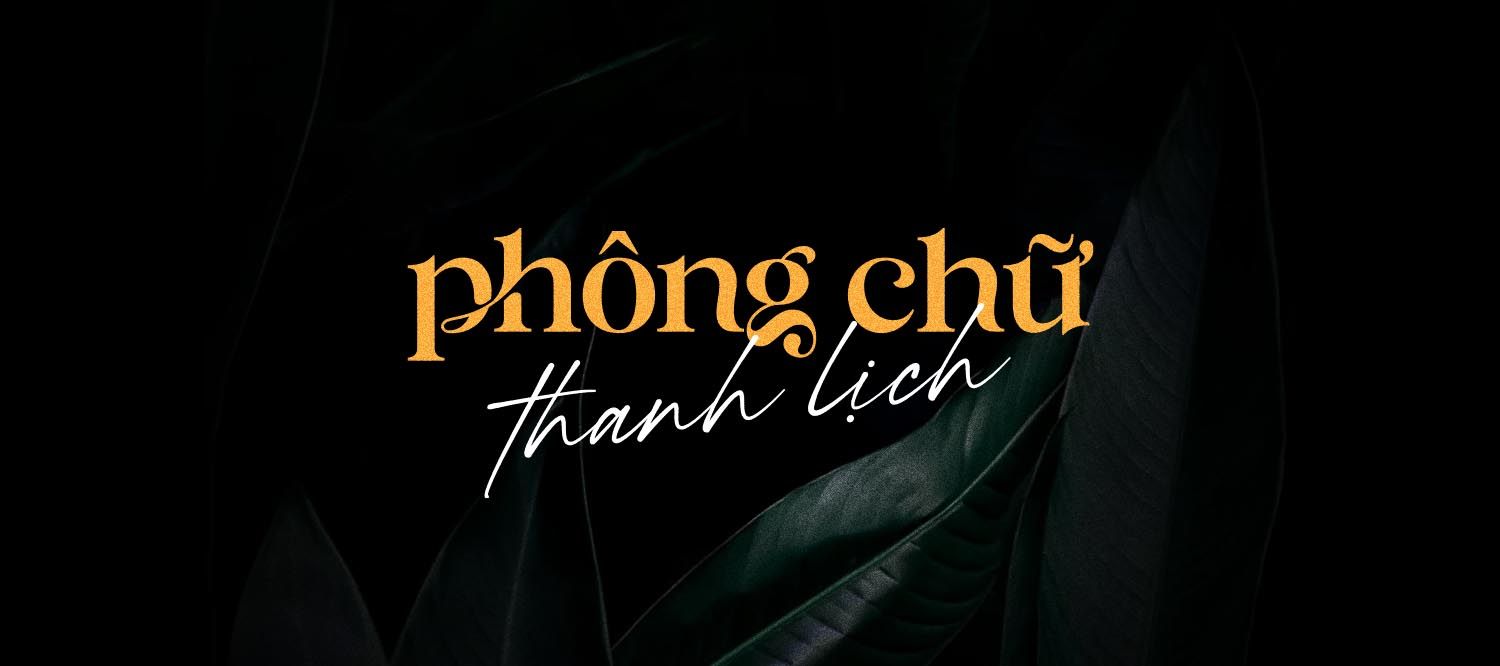
![[Tải Xuống] Bộ Font Chữ Làm Đẹp & Spa Kết Hợp Chữ Ký Viết Tay – Thanh Lịch, Tinh Tế & Cảm Xúc](https://cdn.s99.vn//cloud/X8XpseKt0H75yKqC.jpeg)
Trong lĩnh vực thiết kế thương hiệu, đặc biệt là các ngành liên quan đến spa, làm đẹp, mỹ phẩm hay thời trang, việc chọn lựa font chữ phù hợp đóng vai trò rất quan trọng. Một thiết kế chỉn chu, tinh tế cần đến sự kết hợp hoàn hảo giữa font chữ làm đẹp hiện đại và font chữ viết tay thanh mảnh, giúp truyền tải rõ nét tinh thần thương hiệu: vừa chuyên nghiệp, vừa gần gũi và đầy cảm xúc.
Bài viết hôm nay sẽ giới thiệu đến bạn một combo font chữ cực kỳ ăn ý: sự kết hợp giữa font serif hiện đại và font chữ chữ ký viết tay – như minh họa trong hình ảnh bạn đang xem. Đây là lựa chọn lý tưởng để áp dụng cho logo spa, tiêu đề mỹ phẩm, poster làm đẹp hay cả các ấn phẩm truyền thông cá nhân hoá.
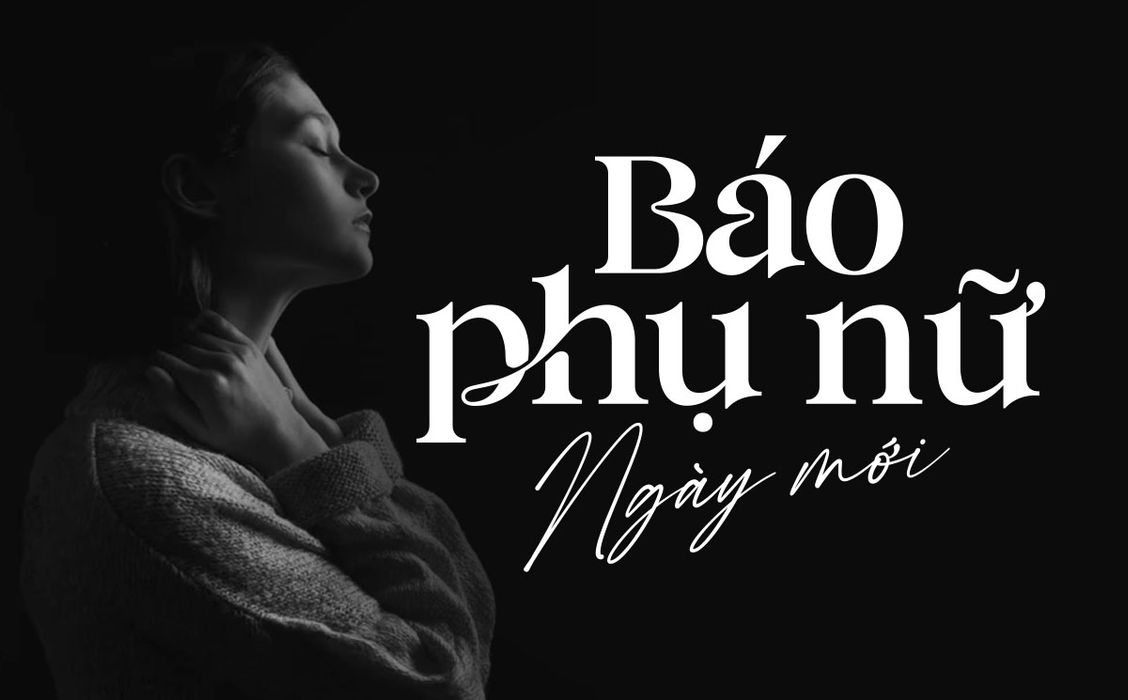
Font chữ chính được sử dụng cho tiêu đề là một kiểu serif hiện đại – một lựa chọn phổ biến trong thiết kế cao cấp. Điểm nổi bật của font này là có độ đậm ấn tượng giúp tiêu đề nổi bật, chân chữ chắc chắn nhưng tinh giản tạo cảm giác thanh lịch, cùng với cấu trúc chữ cái cân đối, dễ đọc và mang lại vẻ chuyên nghiệp.
Trong lĩnh vực spa – làm đẹp, kiểu chữ serif hiện đại là lựa chọn lý tưởng để truyền tải sự chuyên nghiệp và tinh tế. Font này đặc biệt phù hợp khi sử dụng trong thiết kế logo thương hiệu, giúp tạo dấu ấn mạnh mẽ và dễ nhận diện. Bên cạnh đó, nó cũng phát huy hiệu quả trong các tiêu đề brochure spa, mang lại vẻ sang trọng và rõ ràng. Các nhãn mỹ phẩm cao cấp hay ấn phẩm marketing, tạp chí sức khỏe và làm đẹp cũng trở nên chỉn chu, đáng tin cậy hơn khi sử dụng kiểu chữ này như một phần trong hệ thống nhận diện thương hiệu.
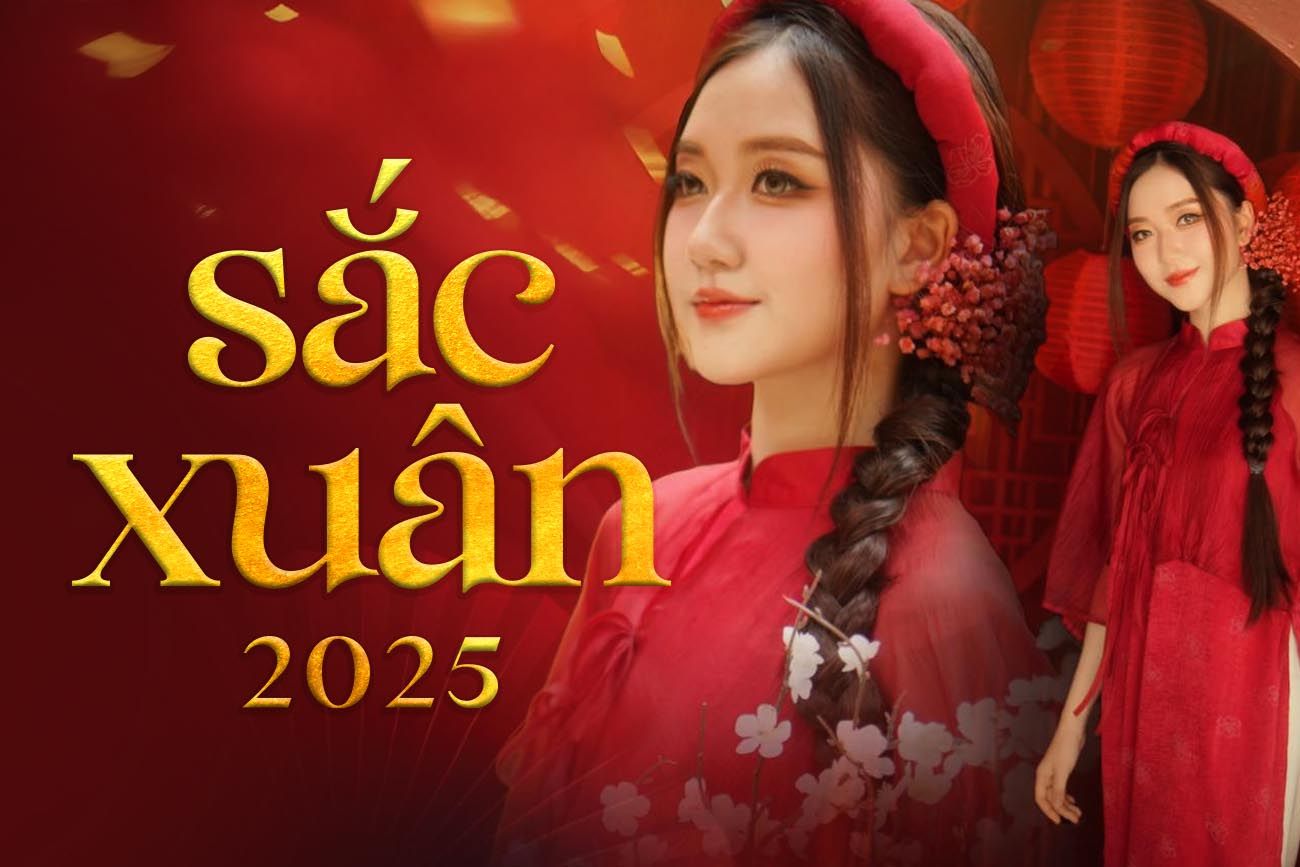
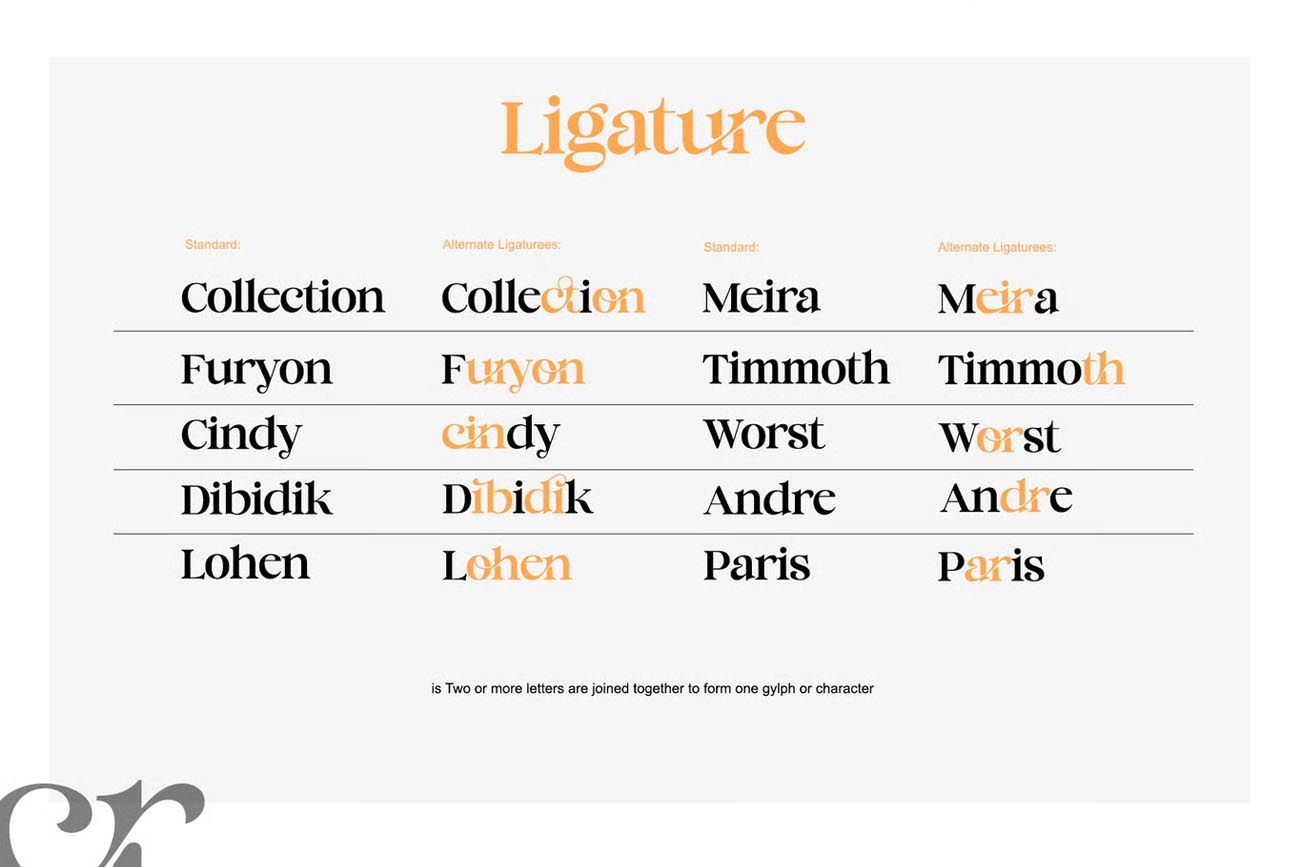
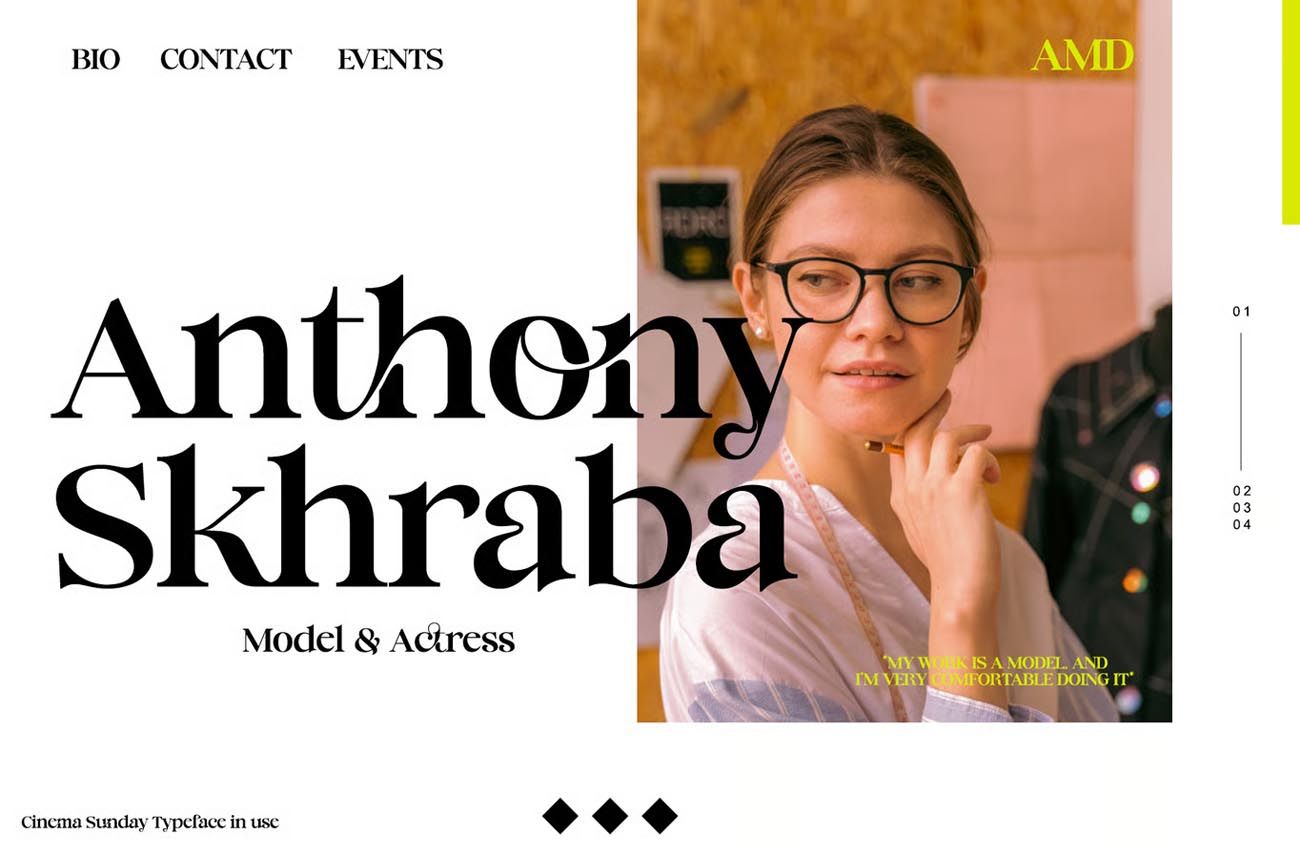
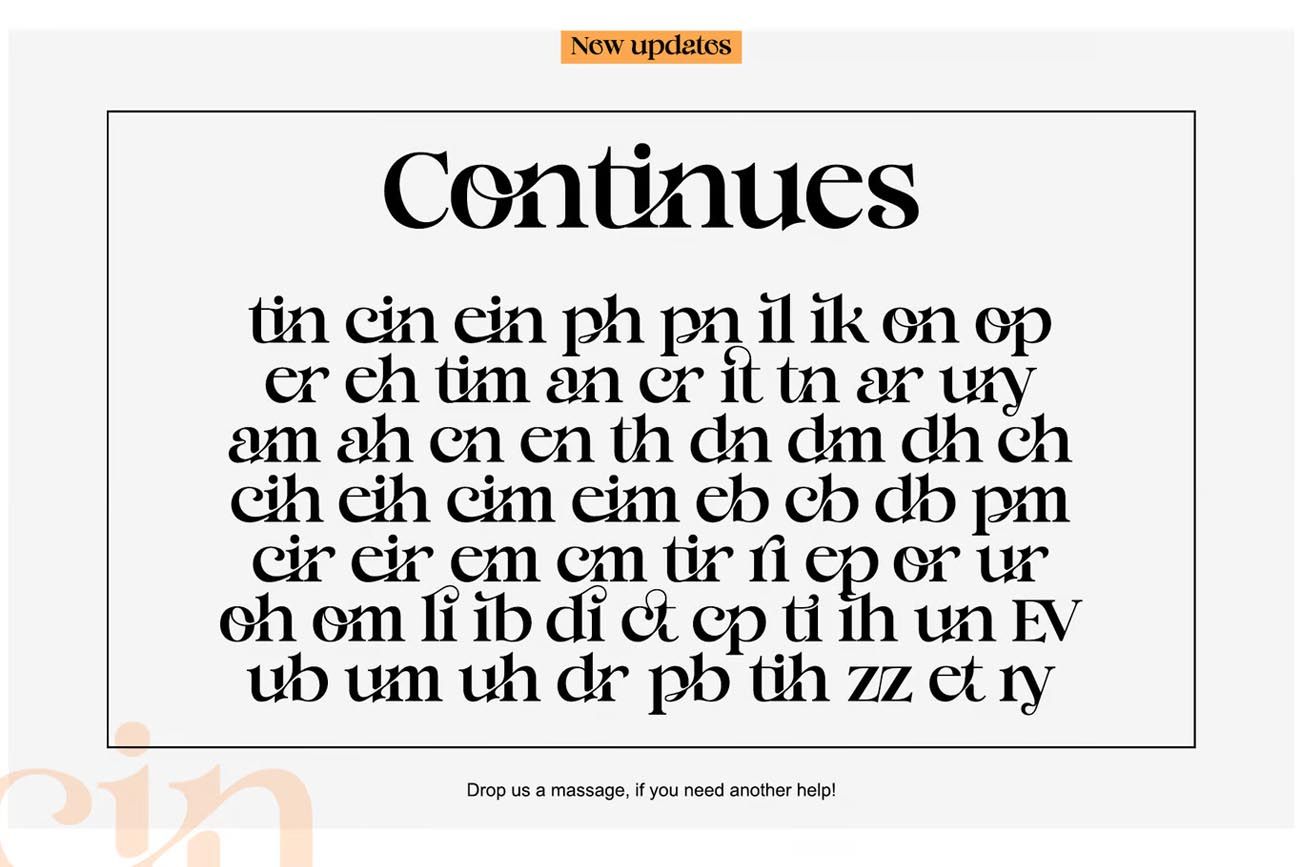
Phần chữ ký – viết tay mảnh, mang đậm chất nghệ thuật và cảm xúc cá nhân. Font này nổi bật với nét bút monoline thanh mảnh, uyển chuyển như chữ ký tay, kết hợp cùng kiểu dáng bay bổng, tạo điểm nhấn nhẹ nhàng và duyên dáng trong thiết kế.
Bên cạnh đó, font mang lại cảm giác tự nhiên, gần gũi, như một lời thủ thỉ của thương hiệu gửi đến người xem. Nhờ vậy, nó không chỉ tạo chiều sâu cảm xúc mà còn làm tăng mức độ kết nối với khách hàng mục tiêu.
Font chữ viết tay dạng chữ ký này đặc biệt phù hợp khi dùng cho slogan spa, tagline thương hiệu làm đẹp, thiệp mời, voucher tri ân, hoặc chữ ký trên poster quảng cáo mỹ phẩm. Ngoài ra, nó cũng rất hiệu quả trong nội dung mạng xã hội, đặc biệt là các thiết kế Instagram hay Facebook mang tính cá nhân hoá.
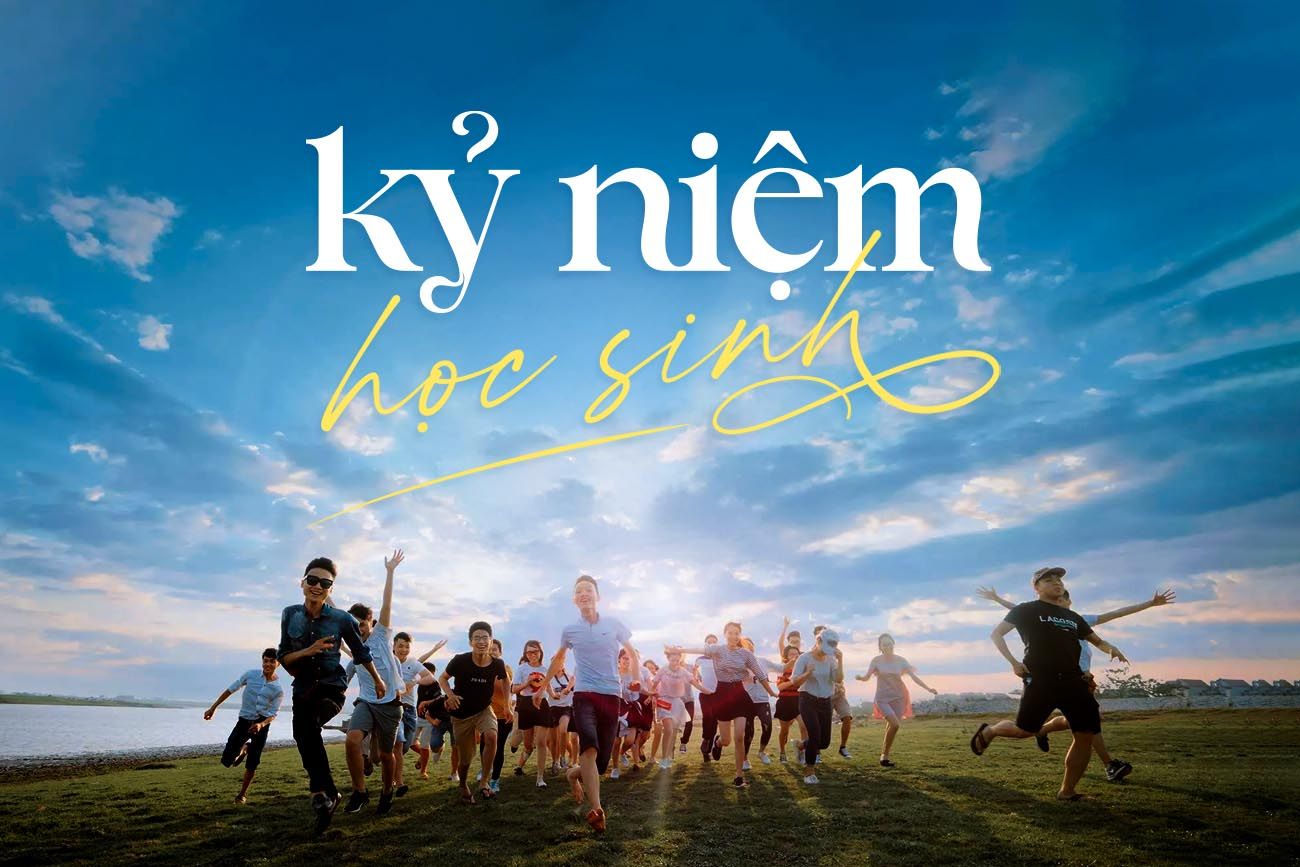
Sự kết hợp giữa font serif hiện đại và font chữ ký viết tay tạo nên điểm nhấn thị giác rõ ràng: một bên mạnh mẽ, chuyên nghiệp – một bên mềm mại, cảm xúc. Đây là lựa chọn lý tưởng cho các thương hiệu làm đẹp muốn vừa sang trọng vừa gần gũi.
Ngoài ra, bộ đôi font này giúp cân bằng giữa chất cổ điển và hiện đại, giữa sự tin cậy và cá tính nghệ thuật – rất phù hợp cho logo spa, tiêu đề mỹ phẩm hoặc ấn phẩm truyền thông ngành làm đẹp.
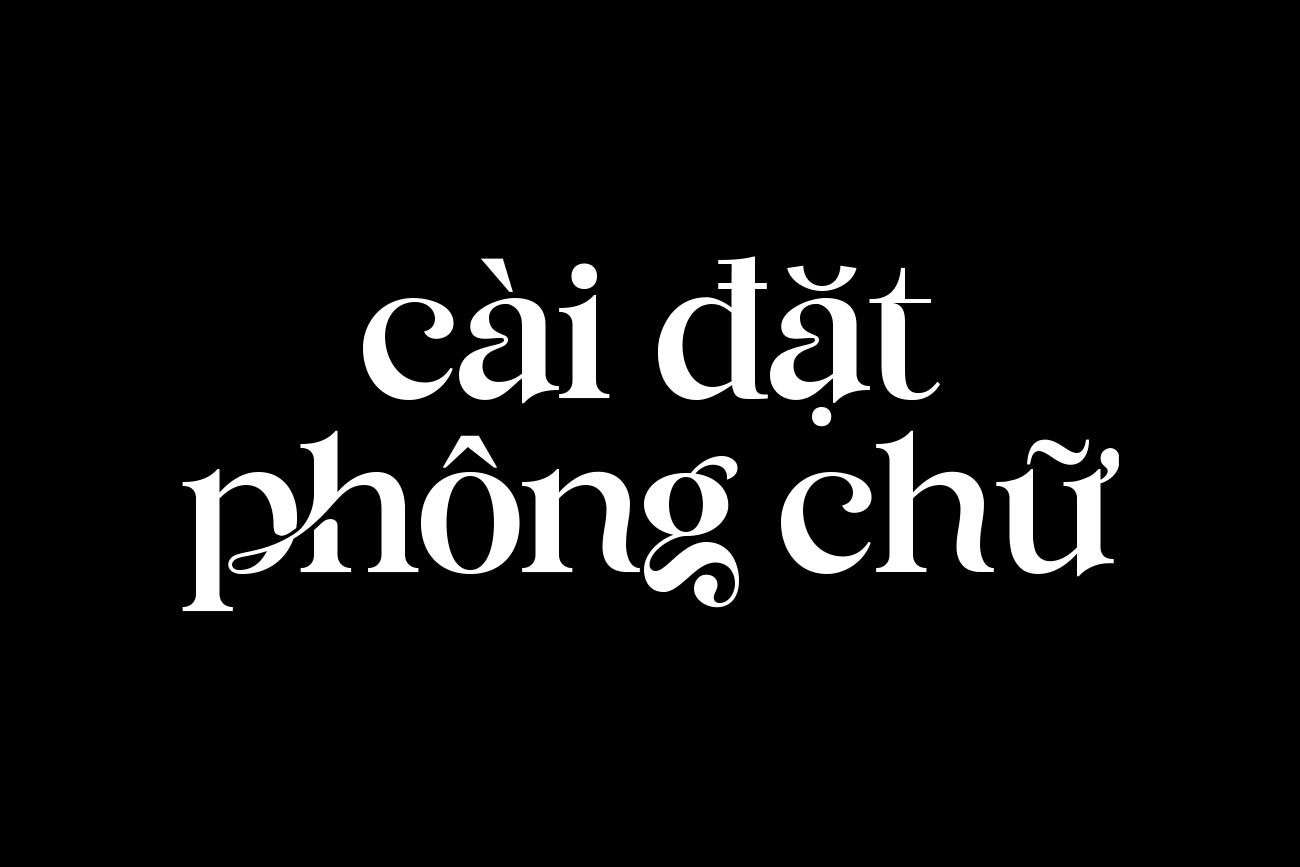
Sự tinh tế trong thiết kế ngành làm đẹp và spa không chỉ đến từ màu sắc, hình ảnh mà còn nằm ở từng chi tiết chữ viết. Việc chọn lựa đúng font chữ làm đẹp – kết hợp giữa một font serif trang trọng và một font chữ viết tay kiểu chữ ký sẽ tạo nên bản sắc riêng, truyền tải thông điệp mềm mại nhưng đầy chuyên nghiệp.
Nếu bạn đang tìm kiếm một bộ font chữ spa cao cấp, vừa sang trọng vừa gần gũi, dễ ứng dụng từ in ấn đến digital – combo font như trong ảnh minh họa là lựa chọn không thể bỏ qua.!